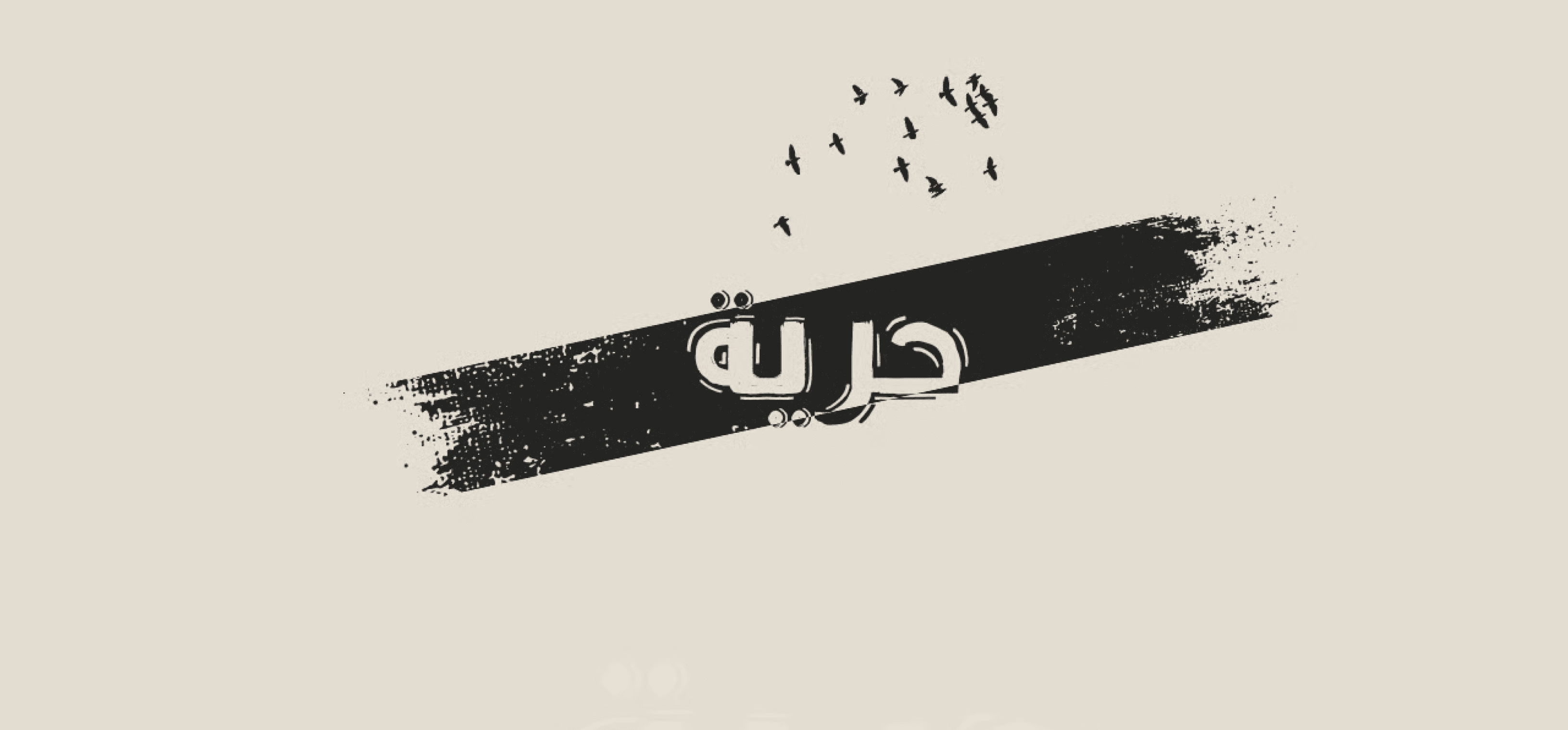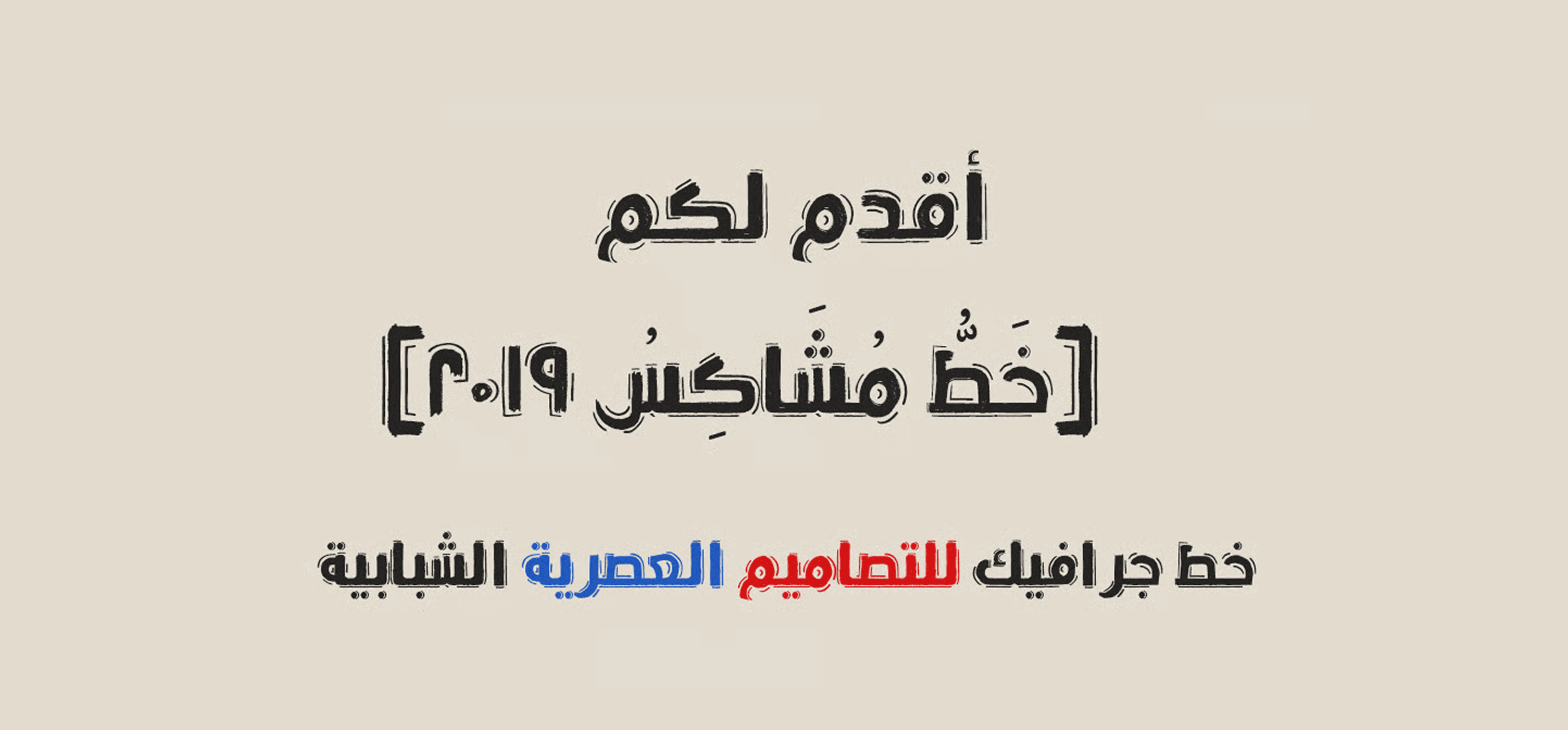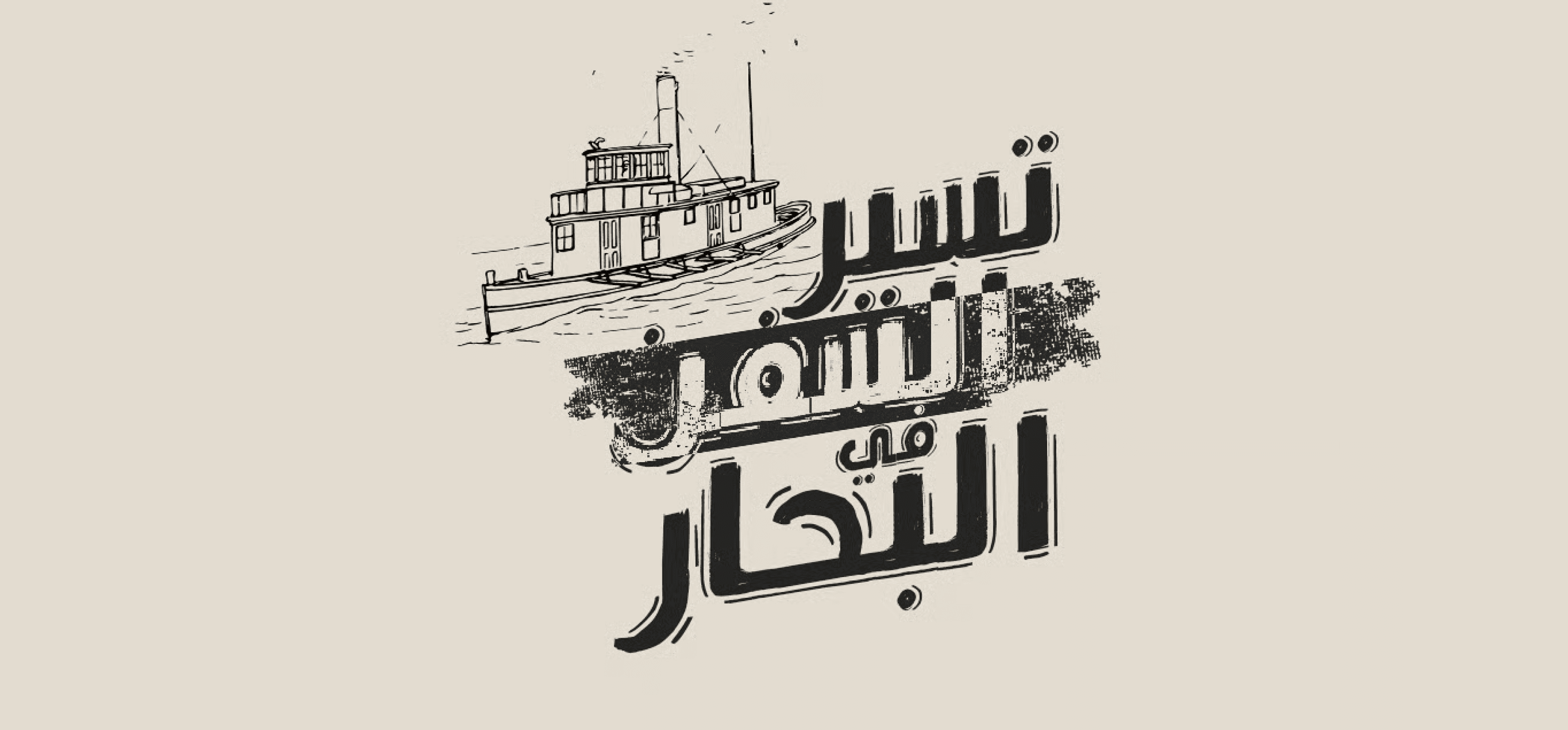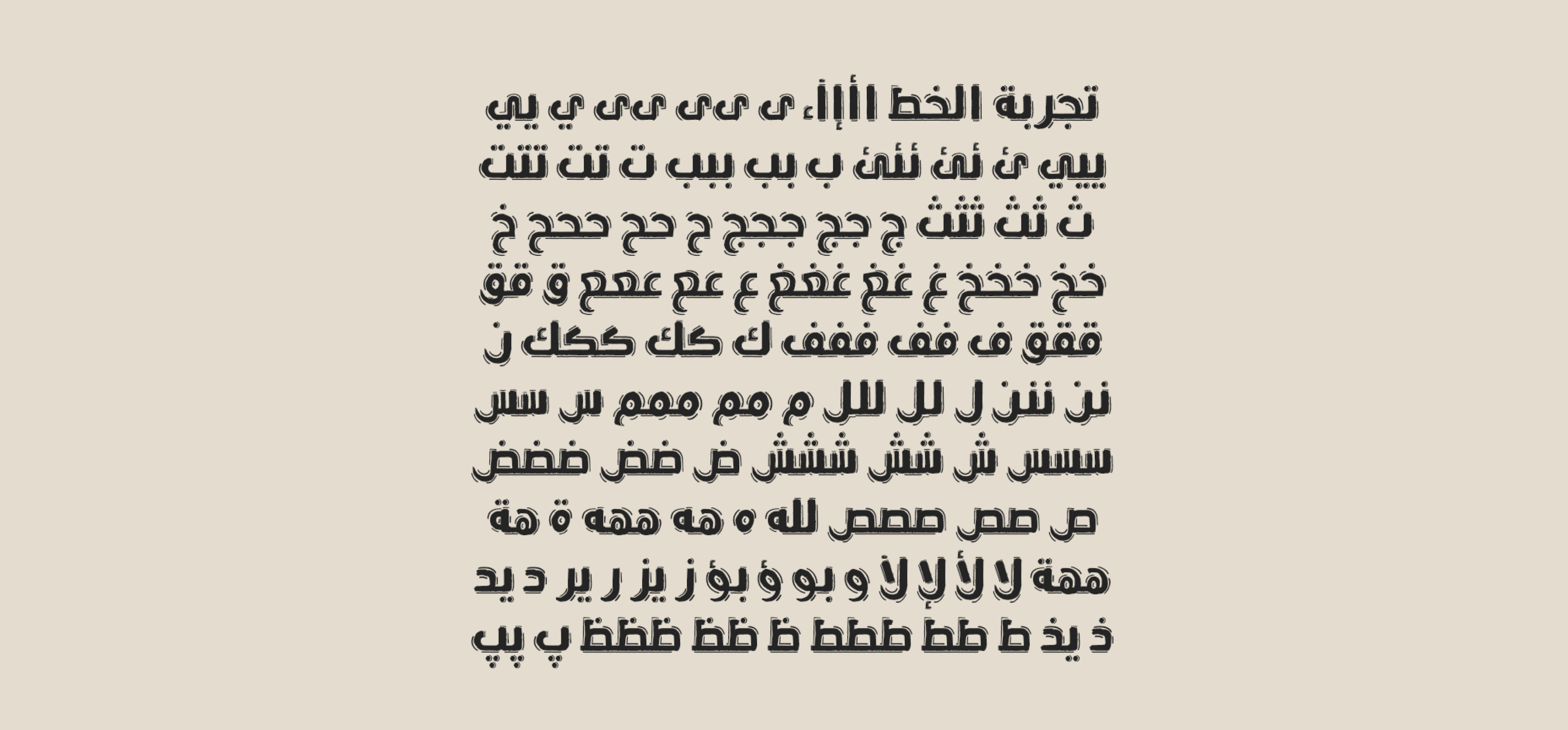
خط مشاكس 2019
أقدمه لكم بأسلوب جرافيكي مميز للتصاميم العصرية الشبابية.
خط جريء وغير تقليدي بتفاصيل حادة ولمسات فنية، يُعد مثاليًا للاستخدام في البوسترات، تصاميم السوشيال ميديا، والشعارات التي تستهدف فئة الشباب.
تم تطويره من قِبل ghanim-font، ويجمع بين الطابع المرح والتأثير البصري اللافت للنظر.